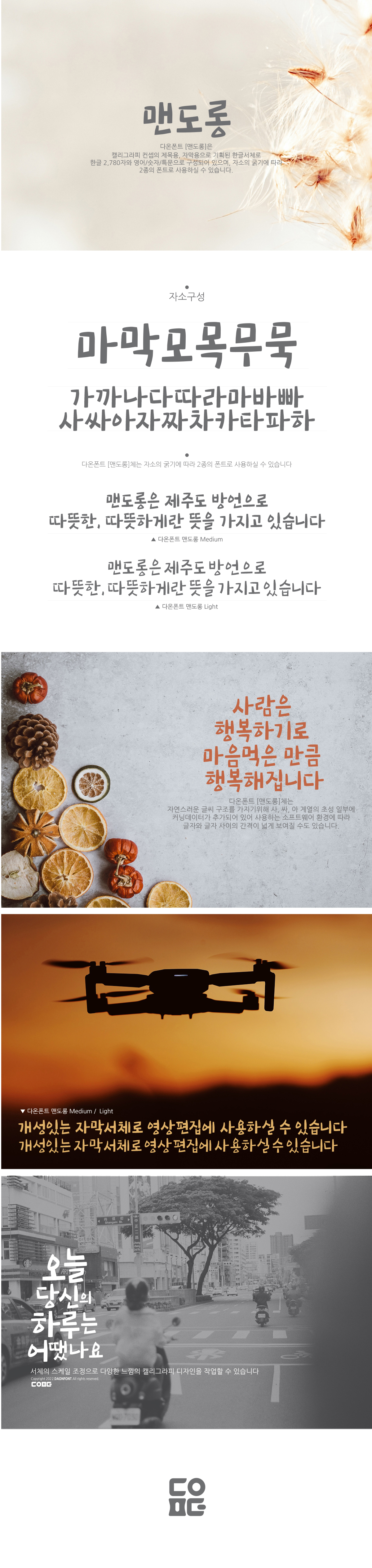
9월 신서체인 다온폰트 "맨도롱"이 업데이트 되었습니다.
다온폰트 "맨도롱"은 캘리그라피 컨셉의 제목용, 자막용으로 기획/제작된 폰트로
한글 2,350+430자의 추가글자와 영어,숫자,특문으로 구성되어 있으며,
자소에 굵기에 따라 2종의 폰트로 사용하실 수 있습니다.